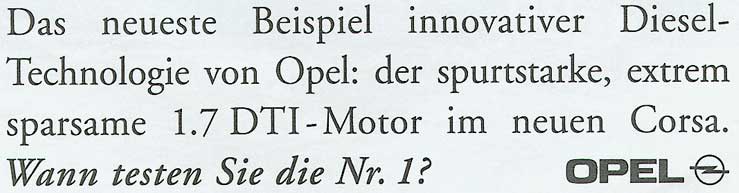
■■■Popular Fonts Ads Recreation: フォント使用例 車広告編 2■■■
最近人気のライノタイプフォントの使用例です!
海外では車広告にどんな書体を使ってるのでしょうか?!
Nissan |
Mitsubishi |
VW |
Opel |
Audi |
Peugeot |
■■■雑誌『デザインの現場』12月号 発売中!! 今回も引続きカーター氏にインタビュー!!3■■■
「定番書体徹底解剖」
デザイナーなら一度は使ったことのある欧文書体を章氏が人気の秘密を探り、オリジナルの書体デザイナーに直接インタビュー!
今月号は既にお読みになりましたか?今回も引続き、 Matthew Carter (マシュー・カーター)氏に色々とインタビューをしています。
前回では、10月号のメールマガジン・章氏に聞こうQ&Aの回答でもでましたが、章氏がとびっきりカッコ良いと思っているGalliard 書体についてかなり詳しく書かれてましたね。今月は、Big Caslon、Georgia 書体について詳しく聞いています。
Big Caslon、Georgia 書体の制作しようと思った理由、制作したきっかけなど・・・章氏だから聞ける質問内容がたくさん掲載してあるので、カーター氏の人柄もわかります。勿論、いつも同様にサンプル図版が多いので 、 見やすく理解しやすいと思います!
■■■ 『The Helvetica Book』 ヘルベチカの本 by 大谷秀映 好評発売中!!!4■■■
もうご存知ですか?書店で綺麗なオレンジ色の本を見ましたか?
皆さんもよ〜くご存知の Helvetica の本が発売されました!
ライノタイプ社の世界ランキングでも常に上位の Helvetica 。
広告宣伝ではかかせない Helvetica 。
日本の市場でも非常に人気の高い Helvetcia 。
何故かHelvetica を使ってしまうという人、いませんか?
でもよくHelvetica の事を知らないあなた!!そんなあなたの疑問が解けるかも?!
今日は2005年11月21日に発売された 『The Helvetica Book』 ヘルベチカの本を紹介致します。
Ex Ponto™
Jovica Veljovic, 1997
Ex Ponto フォントは、Jovica Veljovic 氏がデザインしました。Veljovic 氏の筆跡のリズムを基にしながら切れ味の良い元気なスクリプト体が仕上がっています。この書体は、勢いのある筆跡文字と精巧に作られた優雅なスクリプト文字を組み合わせました。Veljovic 氏は、初めにカリグラフィ文字を下書き用紙に書いた後にギザギザとしている不揃いの先端部分の文字をさらにバランスの摂れた上品な文字へと慎重に修正しました。Ex Ponto フォントは、Light から Bold までの3種類のウェイトを用意しています。もともとディスプレイサイズで使用する為にデザインされた書体ですが、サイズ12ポイントといった小さいサイズでテキストとしても使用できます。活気があって鮮やかさの中にも力強さがある Ex Ponto 書体をポスターやパッケージなどに使用すれば見てる人を釘付けにする事間違いなし!
Ex Ponto™ Pro Light
Ex Ponto™ Pro Regular
Ex Ponto™ Pro Bold
Bix Bats シンボルファミリーは、2003年・アルゼンチン人デザイナー、Victor Garcia 氏がデザインしています。現在、TakeType no.3.1 CDに収録してあります、ディスプレイテキストフォントBix Plain という書体にぴったり合う書体用に補足して作りました。Bix Bats は、4種類のシンボルフォントを収録しています。ほとんどのキャラクターは、半分から下のシンボルが上のシンボルと逆になってるユニークな書体です。ラインを揃えてシンボルフォントをタイプしたり、下の見本のようにシンボルフォントとBix Plain 書体の文字を一緒にして、下と上の部分のカラーを変えたりすると面白いテキストが出来上がります。
下のサンプルにあるようにBix Bats Arrows は、名前の通り矢印のシンボルです。アーチェリーの矢をシンボルにしたフォントからアメリカのリサイクルのシンボルマークを意味するフォントまでたくさんのシンボルフォントを収録しています。又、Bix Bats Funny は、パーティ関連するシンボルフォントがたくさん収録されています。ビールなどのアルコール系フォントから小ウサギちゃんまで何でも揃ってます。Bix Bats Shiny は、夜の空に光り輝く色んな種類の星や輝きを散りばめたシンボルフォントが揃っています。Bix Bats Wired は、現代に必要な電化製品?携帯やメール〜電球まで数多くのシンボルフォントを取り揃えてます。
Bix Bats™ Std Arrow
Bix Bats™ Std Funny
Bix Bats™ Std Shiny
Bix Bats™ Std Wired